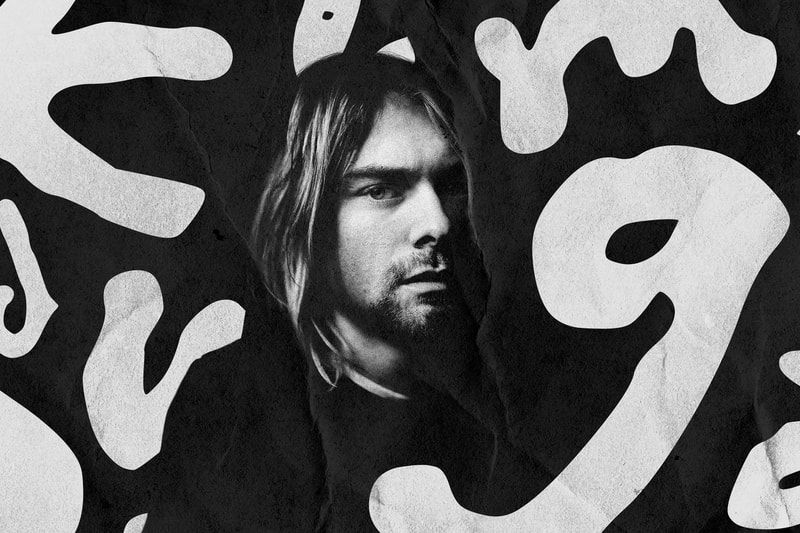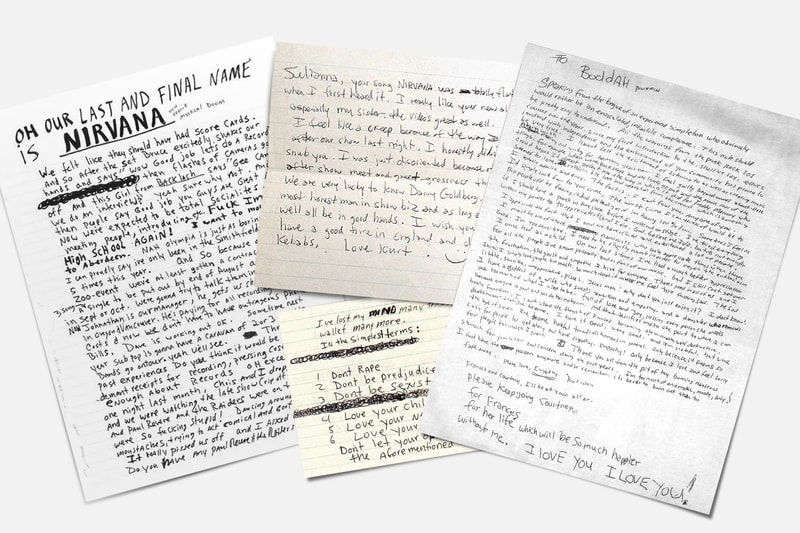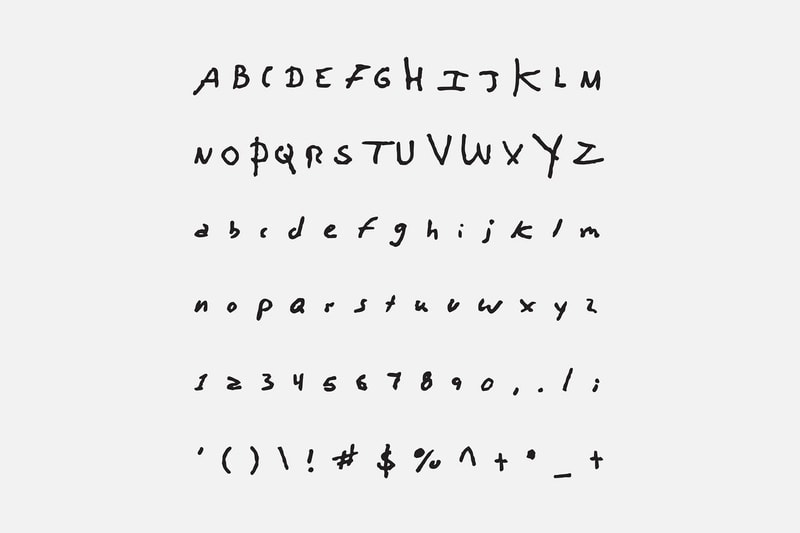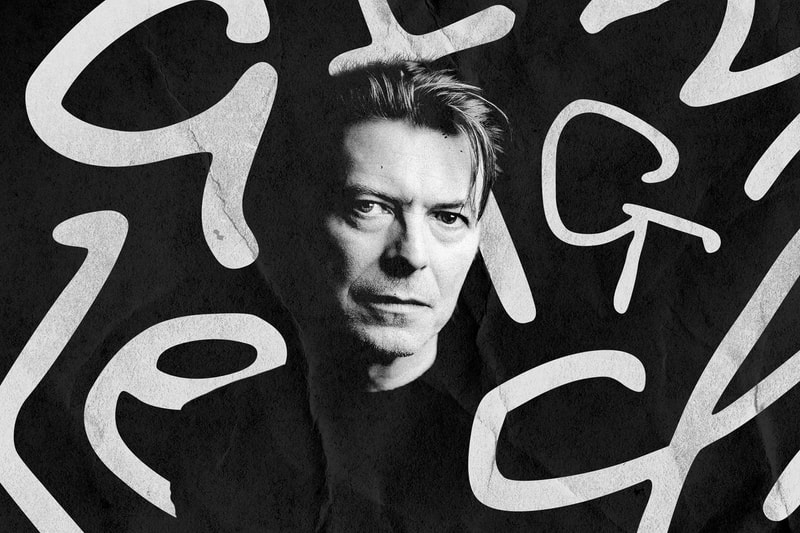
존 레논, 데이비드 보위, 커트 코베인의 친필 편지로 만든 '송라이터 폰트'
무엇을 쓰든 노랫말이 되리.
데이비드 보위, 커트 코베인, 존 레논, 레너드 코헨, 세르쥬 갱스부르 등 전설적인 뮤지션들의 필체가 상용 가능한 폰트로 재탄생했다. 아트 디렉터 니콜라스 다미엔스(Nicolas damiens)와 줄리엔 센스가(Julien sens)가 ‘레전드’ 뮤지션들의 친필 편지와 가사 메모 등에서 발췌한 서체를 디지털 폰트로 제작한 ‘송라이터 폰트’다. 커트 코베인 체의 무심한 듯한 ‘c’나 작은 ‘i’의 경우, 그의 유서를 바탕으로 제작되었기에 겸허한 마음마저 든다. 존 레논의 필체는 정갈함이, 보위의 서체는 그래픽 같은 화려함이, 레너드 코헨은 그만의 독특한 스타일이 매력이다. 다섯 가지 송라이터 폰트 모두 songwriterfonts.com에서 다운로드 할 수 있다. 이런 폰트라면, 어떤 글을 타이핑하더라도 한 곡의 노랫말처럼 만들어주지 않을까?